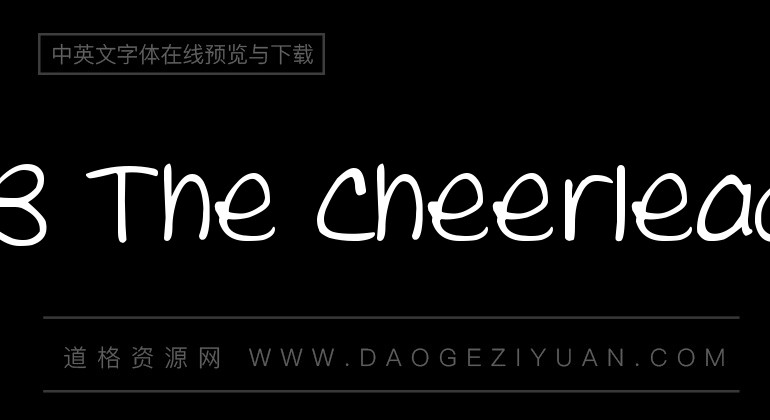
DJB The Cheerleader
DJB The Cheerleader是一种手写字体,其特点是活泼、有趣、充满能量。这种字体由Darcy Baldwin设计,旨在为卡片、海报、海报、招贴、标语等文化艺术作品带来更多的生气和活力。 DJB The Cheerleader 字体中的字母和数字都是手写风格,略带倾斜、有点不整齐,这使得它能够传达出一种充满个性的感觉。该字体还包含一些符号和装饰,例如心形、星形、泡沫等等,这些能够有效地丰富作品的视觉效果。 总的来说,DJB The Cheerleader 字体适用于需要强调个性、活力和青春气息的设计场合。
DJB The Cheerleader是一款非常不错的手写艺术字体,具有很好的视觉感,适合于文化类的宣传设计、商业类品牌的广告和产品包装设计以及个性化文字排版等较多场景。